Zwiebelfisch
1. Typografischer Fachausdruck aus dem gewerbespezifischen Sprachschatz dspr. Schriftsetzer und Drucker aus der Periode des materiellen Schriftsatzes mit physischen Drucktypen aus Metall (z.B. aus einer Blei-Zinn-Antimon-Kupfer-Legierung) für ein gedrehtes Blockadezeichen – einen Fliegenkopf – welches als Konsultationszeichen beispielsweise auf eine Korrektur oder einen Ersatzbuchstaben hinweist, das nach der Endkorrektur im Zuge der Deblockade nicht entfernt und deshalb irrtümlich gedruckt wurde.
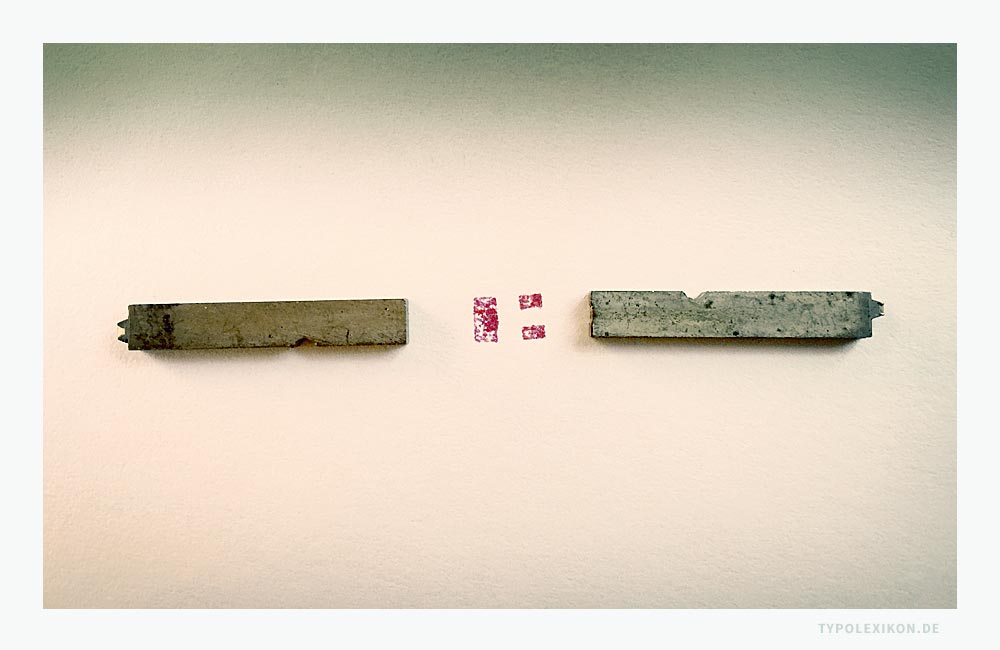
Der Abdruck des »Fußes« eines Schriftkegels wird in der Typografie als »Fliegenkopf« bzw. als »Blockadezeichen« bzw. bei fehlerhafter Deblockade als »Zwiebelfisch« bezeichnet. Je nach Schriftguss kann er aus einem oder zwei Rechtecken bestehen, je nachdem, ob der Kegel eine Fußrille besitzt oder nicht. Im Beispiel links: Kegel ohne Fußrille mit einem rechteckiger Abdruck. Rechts: Kegel mit Fußrille mit einem Abdruck aus zwei Rechtecken.
2. Typografischer Fachausdruck aus dem gewerbespezifischen Sprachschatz dspr. Schriftsetzer und Drucker aus der Periode des materiellen Schriftsatzes mit physischen Drucktypen aus Metall (z.B. aus einer Blei-Zinn-Antimon-Kupfer-Legierung) für gedruckte Buchstaben innerhalb eines geschlossenen Schriftsatzes, die fälschlicherweise aus einer anderen Schriftgattung, Schriftart, Schriftgarnitur oder Schriftschnitt stammten bzw. ein »zusammengefallenes Stück Satz von verschiedenen Schriften« 1)
Ursache für derartige Schriftsatzfehler waren im Setzkasten bzw. Satzkastenfach deplatzierte – also falsch abgelegte – Drucktypen. Schriftsatzfehler dieser Art mit Bleilettern innerhalb einer Schriftfamilie und -garnitur sowie innerhalb des Blindmaterials (z.B. Spatien) wurden als »Fisch(e)« bezeichnet. 2)
3. »Der Zwiebelfisch, eine kleine Zeitschrift für Buchwesen und Typografie« bzw. »Der Zwiebelfisch, eine kleine Zeitschrift für Geschmack in Büchern und anderen Dingen« (Titel nach dem Ausscheiden von Franz Blei). Periodische Reklamehefte des Hyperion-Verlags (später Hans von Weber Verlag), die in München von 1909 bis 1933 von Hans von Weber (1872–1924) bzw. vom Hans von Weber Verlag und von 1934 bis 1948 von Dritten herausgegeben und überwiegend bei Poeschel & Trepte in Leipzig produziert wurden.
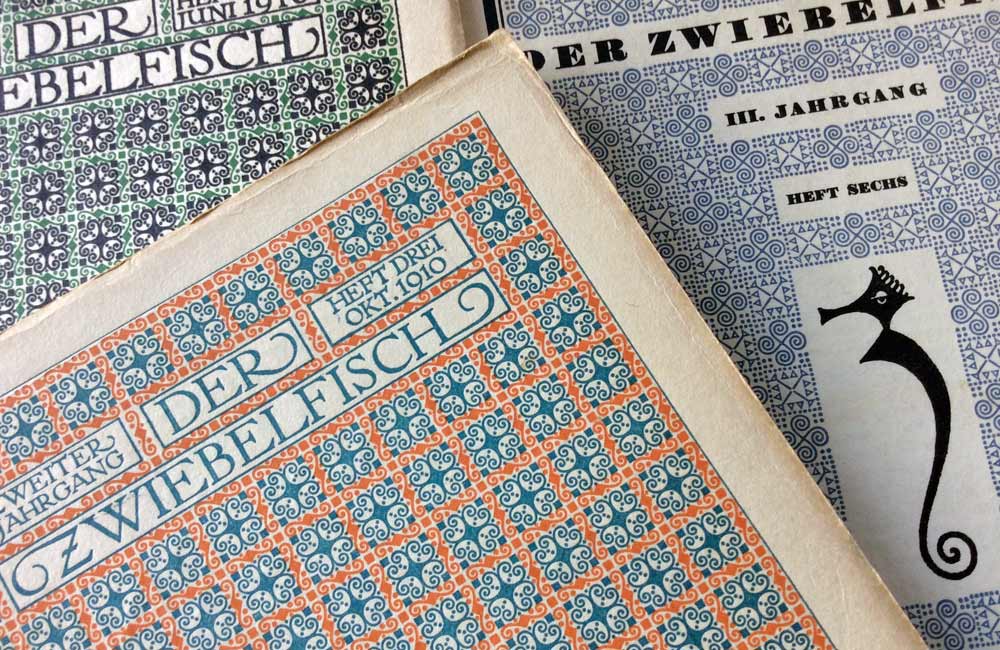
Titelseiten »Der Zwiebelfisch« (1909 bis 1933), Heft 1 und 3 aus dem Jahr 1910 und Heft 6 aus dem Jahr 1911. Gründungsherausgeber Hans von Weber (1872–1924). Quelle: Sammlung Wolfgang Beinert, Berlin. www.typolexikon.de